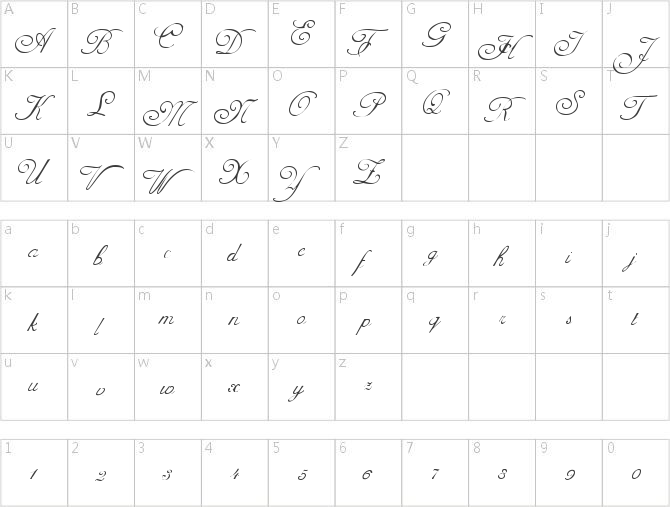
AdineKirnberg-Regular
AdineKirnberg-Regular介绍
AdineKirnberg-Regular字体字库是一款让人赏心悦目、百看不厌的英文字体,适合各类广告和产品包装设计应用,字体大小0.03MB,格式为ttf字体,上传用户是1733150348,作者/版权方为未知